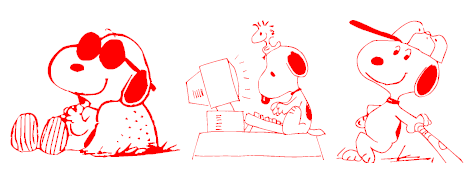
Font Dingbat atau font simbol selalu menarik untuk dikoleksi. Selain bisa mempercantik tampilan karya yang dibuat, kita juga bisa menghemat waktu dan tidak perlu repot untuk menggambar. Bahkan juga ada dingbat font yang dapat berfungsi sebagai border atau pigura, seperti font Floral Settings.
Berikut ini adalah kumpulan dingbat font berbagai tokoh kartun dan film, seperti Mickey Mouse, Snoopy, Harry Potter, Pokemon, South Park dan juga simbol lain seperti bunga, elemen musik, peta, dan berbagai ekspresi wajah.
- Azudings 1
- Dancefloor Exit
- Face it dan Face Off
- Floral Settings
- GeoBats
- Harry Potter and the Dingbats
- Mickey Mousebats
- Music Elements
- Pokemon Kiddy Ding
- Peanuts Gang Dings
- Snoopy Dings
- South Bats
- So Ccsakura